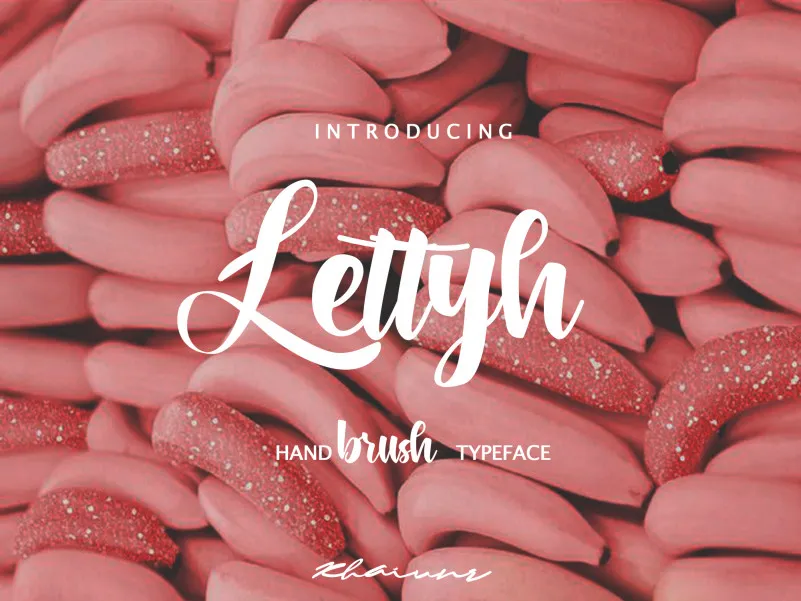
Lettyh Brush Font – Fonte Grátis
Lettyh Brush Font – Download Grátis
Lettyh Brush Font
A Lettyh é uma deliciosa fonte à mão escrita que traz charme único ao seu design. Inspirada no estilo contemporâneo deste traço, ela se destaca como um recurso incrivelmente divertido e criativo. Através de sua elegância peculiar, a fonte ‘Lettyh Brush Font’ proporciona uma sensação leve e descontraída que certamente cativará seu público-alvo. Para designers e estilistas em busca de algo novo e emocionante para adicionar ao seu próximo projeto, o estilo da Lettyh é sem dúvida um marco inovador.
Designer: khaiuns